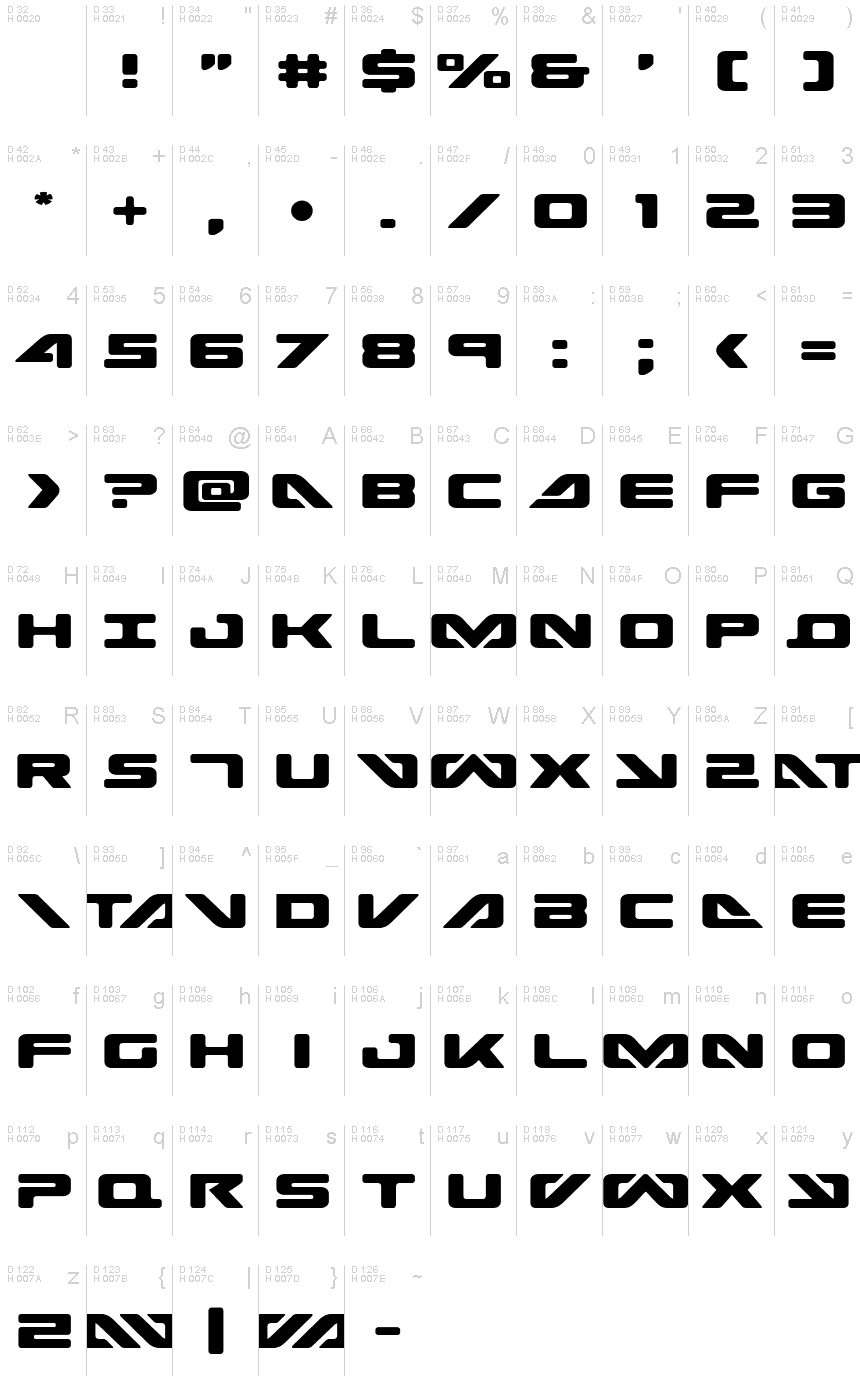
Zanurz się w cyfrowe głębiny z Sea-Dog, odważnym fontem typu display, stworzonym przez kreatywnego Daniela Zadorozny’ego z Iconian Fonts. Ten futurystyczny krój wyróżnia się ekstremalnie szerokimi literami, które natychmiast przyciągają wzrok, zapewniając, że Twój przekaz nie tylko się wyróżni, ale także będzie emanował siłą i nowoczesnością. Estetyka Sea-Dog tkwi w jego zdolności do projektowania innowacji i przyszłościowego myślenia, co czyni go idealnym wyborem do projektów, które chcą prezentować nowatorskie pomysły lub być na szczycie trendów w projektowaniu.
Dzięki swojej solidnej grubości i dominującej obecności, Sea-Dog sprawdza się znakomicie w tytułach, nagłówkach i wszędzie tam, gdzie chcesz, aby tekst wywierał potężny wpływ. Niezależnie od tego, czy chodzi o branding dla startupów technologicznych, materiały promocyjne dla filmów sci-fi czy dynamiczne interfejsy cyfrowe wymagające futurystycznego sznytu, Sea-Dog jest idealnie dopasowany, by dodać Twoim kreatywnym przedsięwzięciom nutkę wyrafinowania. Niech ten krój pisma będzie latarnią morską, która poprowadzi Twoich odbiorców przez wizualną podróż, którą dla nich przygotowałeś.